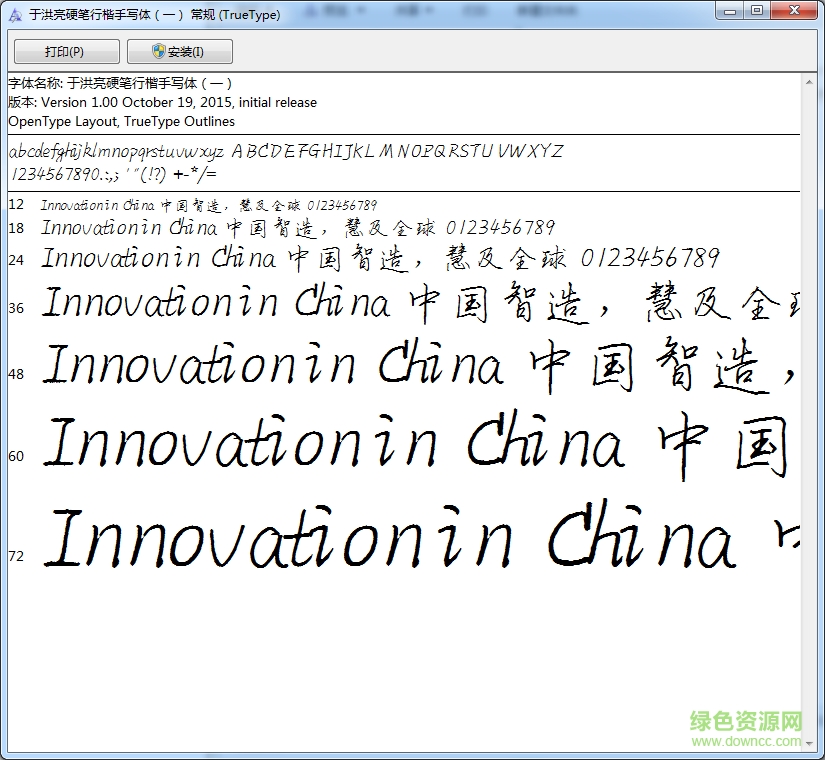
于洪亮硬筆行楷是一款非常有個(gè)性的鋼筆手寫字體,字體纖細(xì)簡單大方,支持不同內(nèi)容輸入顯示,廣泛使用于多種行業(yè)領(lǐng)域??靵砭G色資源網(wǎng)下載體驗(yàn)吧!
于洪亮硬筆行楷手寫字體是一款手寫風(fēng)格的書法字體,字體書寫流暢,字形大方,整體效果十分出色,適合應(yīng)用于廣告設(shè)計(jì)、名片設(shè)計(jì)等方面,需要的話可以來下載使用。